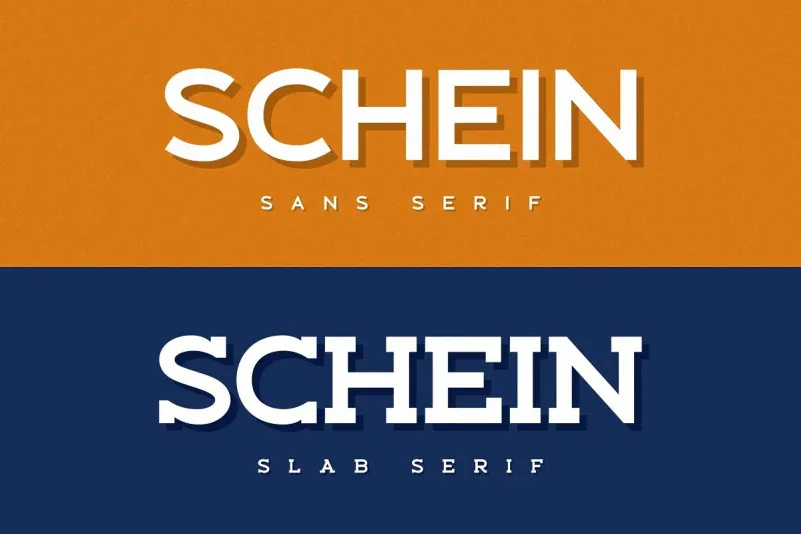
A Schein Font é uma elegante slab serif que traz vida à tipografia moderna e minimalista. Inspirada nas logomarcas simpáticas dos tempos atuais, a Schein adquire um ar futurista e tecnológico ao destacar visivelmente o design gráfico em diversos contextos. Seu visual arredondado e sua geometria simplificada oferecem uma ótima opção para uso tanto no cabeçalho quanto nas páginas de texto, tornando-a perfeitamente adaptável a um amplo espectro de projetos como templates, brochuras, vídeos, marcas publicitárias, logotipos e mais. Não importa o formato ou tamanho do projeto que você está desenhando com essa fonte, ela se destaca como uma escolha ideal para os profissionais de design em busca de um estilo único e moderno.